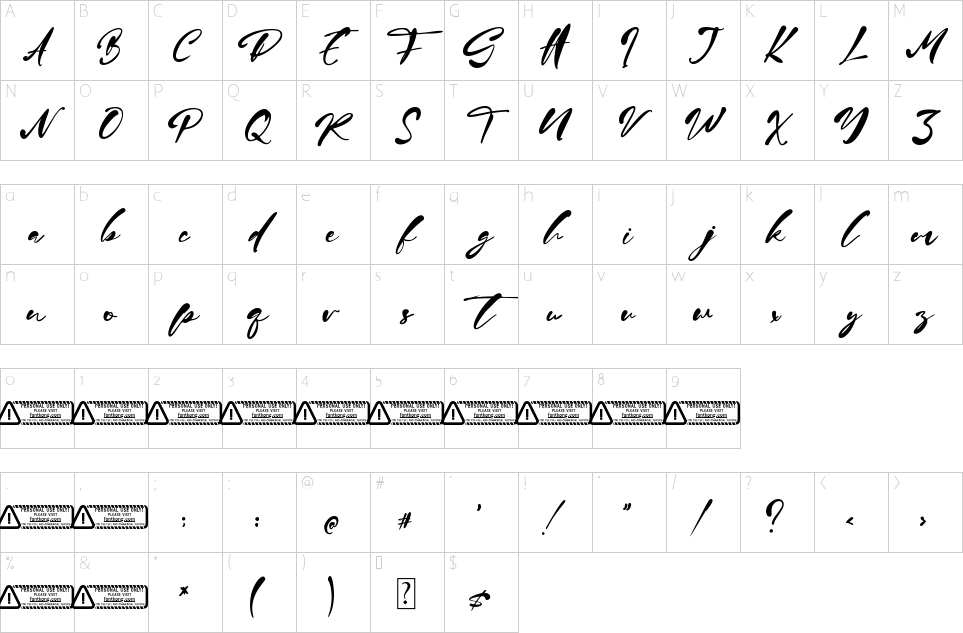
A fonte Jason Mary é uma escolha adequada para aqueles que buscam um estilo elegante e sofisticado. Desenvolvida pela Font Kong, essa fonte está disponível tanto para usuários de Windows quanto para Mac. Com seu design cuidadosamente elaborado, Jason Mary oferece um equilíbrio perfeito entre modernidade e refinamento, fazendo-a uma opção popular entre designers gráficos e profissionais digitais em todo o Brasil. O uso desta fonte pode tornar suas criações ainda mais interessantes e personalizadas, especialmente se estiver buscando adicionar um toque de elegância a seus projetos. Com 1.697 downloads desde sua disponibilização, Jason Mary já provou ser uma escolha segura para quem busca qualidade em suas fontes gratuitas. Inclua esta fonte em seu próximo projeto e experimente como ela pode enriquecer o visual de seus materiais digitais. Seja um designer gráfico ou simplesmente criativo no dia a dia, Jason Mary está à disposição para tornar sua comunicação mais sólida e sofisticada.